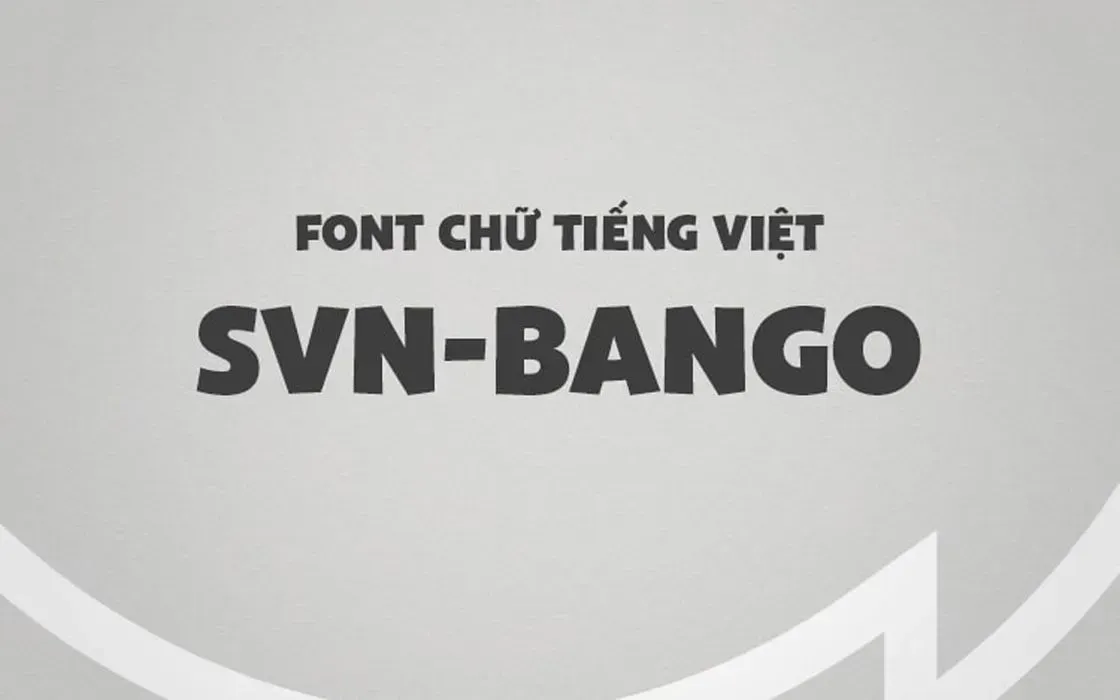
SVN Bango là một kiểu font sans-serif (không chân) mang phong cách display, nổi bật với hình dáng béo tròn, dày dặn và đầy năng lượng. Từng ký tự trong font đều có độ nở lớn, tạo cảm giác tròn trịa, chắc chắn và rất dễ thu hút ánh nhìn. Thiết kế có phần ngộ nghĩnh nhưng vẫn giữ được sự rõ ràng, nên đặc biệt phù hợp với các thiết kế mang tính giải trí, quảng cáo, trẻ em hoặc sản phẩm đại chúng.
Font gốc Bango Pro được thiết kế bởi Dieter Steffmann – một nhà thiết kế người Đức nổi tiếng với nhiều bộ font retro và display độc đáo. Bango mang đến cảm giác thân thiện, vui nhộn nhưng không kém phần hiện đại, rất phù hợp cho các tiêu đề bắt mắt, poster, bao bì sản phẩm hoặc biển hiệu thương mại.
Bản Việt hóa SVN Bango do nhóm SVN Fonts thực hiện – đây là một trong những nhóm Việt hóa font chuyên nghiệp hàng đầu tại Việt Nam. Bộ font đã được tinh chỉnh cẩn thận, bổ sung đầy đủ dấu tiếng Việt, đảm bảo tính thẩm mỹ và khả năng sử dụng tốt trên các phần mềm thiết kế như Illustrator, Photoshop, Canva hoặc Word.
Nếu bạn đang tìm một font chữ không chân có phong cách vui nhộn, cứng cáp và tạo được hiệu ứng thị giác mạnh, SVN Bango chắc chắn là lựa chọn tuyệt vời cho các thiết kế cần truyền tải năng lượng tích cực, sự sáng tạo và nét thân thiện.